Canvaで使える筆記体おすすめ5選|用途別に合うフォントがすぐ分かる
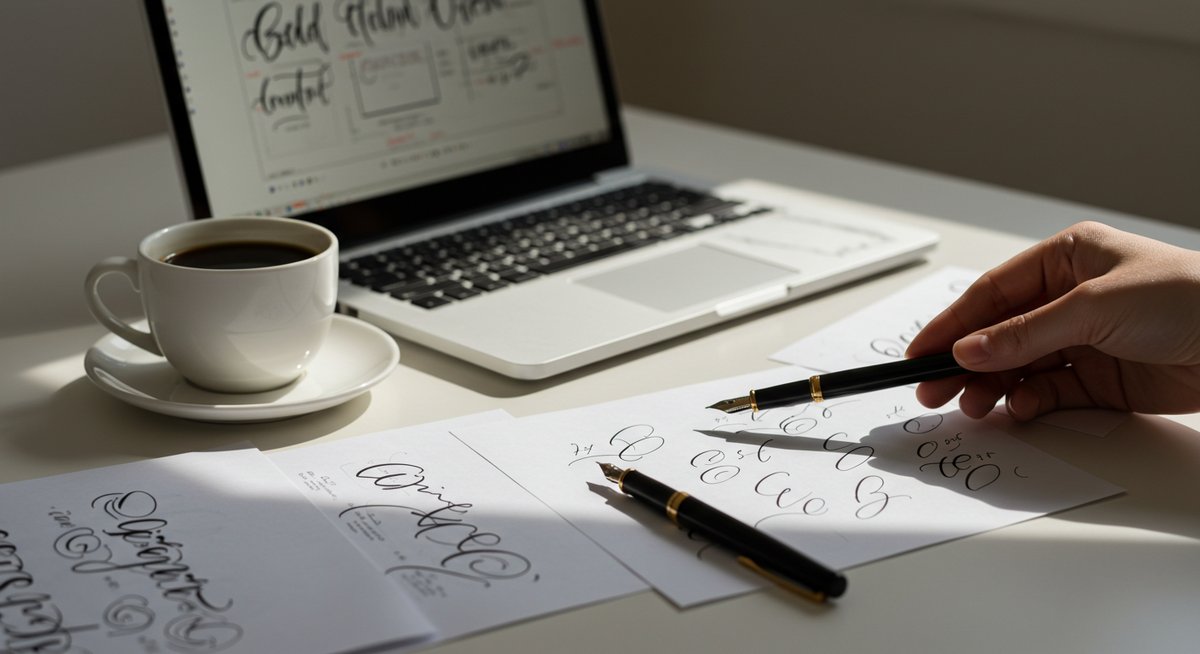
anvaで使える筆記体フォントを選ぶときは「見た目の好み」と「用途」を両方見て決めると失敗が少ないです。この記事では、用途に合わせたおすすめフォントや使い方のポイントをわかりやすく紹介します。どの場面でどんな印象になるかをイメージしながら選べば、デザインの仕上がりがグッとよくなります。
迷わず選べる Canvaで使う筆記体のおすすめ5選
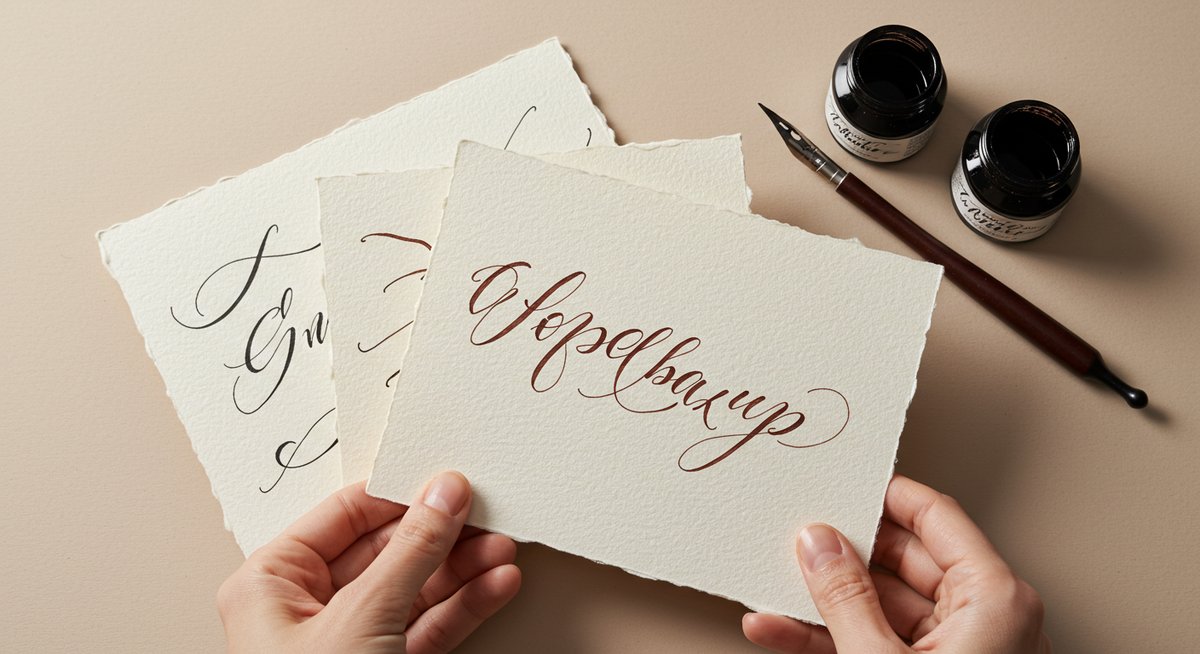
どれを使えば良いか迷ったときに頼れる筆記体を5つピックアップしました。それぞれの特徴と向いている用途を短くまとめています。まずはここから試してみると失敗が少ないですよ。
Allura 無料で上品な定番フォント
Alluraは細めで流れるような線が魅力の筆記体です。角が柔らかく、文字同士のつながりが自然なので、上品で落ち着いた印象を与えたいときに向いています。ロゴや見出し、ウェブサイトのアクセントに使うと、しっかりした高級感を出せます。
読みやすさも比較的よく、小さめのサイズでも崩れにくいのが特徴です。文字間隔を少し詰めるだけで統一感が出るので、見出しやバナーのアクセントにおすすめです。色はダーク系や落ち着いたトーンと相性が良く、シンプルな背景に置くと映えます。
使う場面の例としては、ショップのブランドロゴ、ギフトカード、ブログの見出しなどが挙げられます。フォント自体が主張しすぎないため、他の要素と合わせやすい点も魅力です。
Alex Brush 上品で読みやすい筆記体
Alex Brushは比較的太めの線で、筆致がはっきりしている筆記体です。曲線が滑らかで視認性が高く、装飾的でありながら読みやすさを保ってくれます。そのため、タイトルや重要なフレーズに使うと効果的です。
文字の輪郭がはっきりしているので、背景が多少賑やかでも視認性を確保しやすいです。大きめの見出しや告知バナーに向いており、色を濃くすることでさらに存在感を出せます。行間や文字間を調整すれば、親しみやすい印象からエレガントな印象まで幅広く対応できます。
ブランド名や商品名を目立たせたいとき、又はイベントタイトルなどで使うと、読みやすさとデザイン性の両方を満たせます。
Pacifico カジュアルで親しみやすい筆記体
Pacificoは丸みを帯びた手書き風の筆記体で、明るくフレンドリーな雰囲気を作りやすいフォントです。堅苦しくならないので、カジュアルなショップロゴやSNSの見出しにぴったりです。
太めの線と丸い形状は、小さな画面でも視認性が高く、親しみやすさを強調したいときに便利です。背景に写真を使う場合は、コントラストを強めに取ると読みやすくなります。色使いもポップなトーンに合わせやすく、若い層向けのデザインに向いています。
メニューや商品ラベル、イベント告知など、気軽さや楽しさを伝えたい場面で活躍します。装飾を控えめにしてフォントを主役にする使い方がおすすめです。
Pinyon Script 華やかに飾る見出し向け
Pinyon Scriptは装飾性の高い筆記体で、華やかな印象を与えるのに向いています。しなやかなカーブと装飾的な終端が特徴で、特別な場面や格式感が欲しいデザインにマッチします。
大きめの見出しや招待状のタイトルに使うと、エレガントで印象的な雰囲気を演出できます。繊細なラインが多いので、小さなサイズには向きませんが、大きく表示することで美しさが際立ちます。背景はシンプルにして、フォントのディテールを見せると効果的です。
色はゴールド系やダークカラーと合わせると上品さが増します。結婚式の招待状や高級感を出したい商品パッケージなどに向いています。
Halimum 小さなアクセントに使いやすい筆記体
Halimumは控えめで細やかな筆記体です。大きく主張しすぎないため、ロゴの一部やワンポイントのアクセントに最適です。柔らかく落ち着いた線で、全体のバランスを壊さずに雰囲気を添えてくれます。
小さめの注釈やサブタイトル、名刺の一部などに使いやすく、他のフォントと組み合わせても喧嘩しにくいのが利点です。色は淡めのトーンでも馴染みやすく、ページのアクセントとして自然に溶け込みます。
細めのフォントなので、背景とのコントラストに気をつけると見やすさを保てます。全体のデザインを邪魔せず、ちょっとした個性を出したいときに役立ちます。
用途で選ぶと失敗しない筆記体の選び方
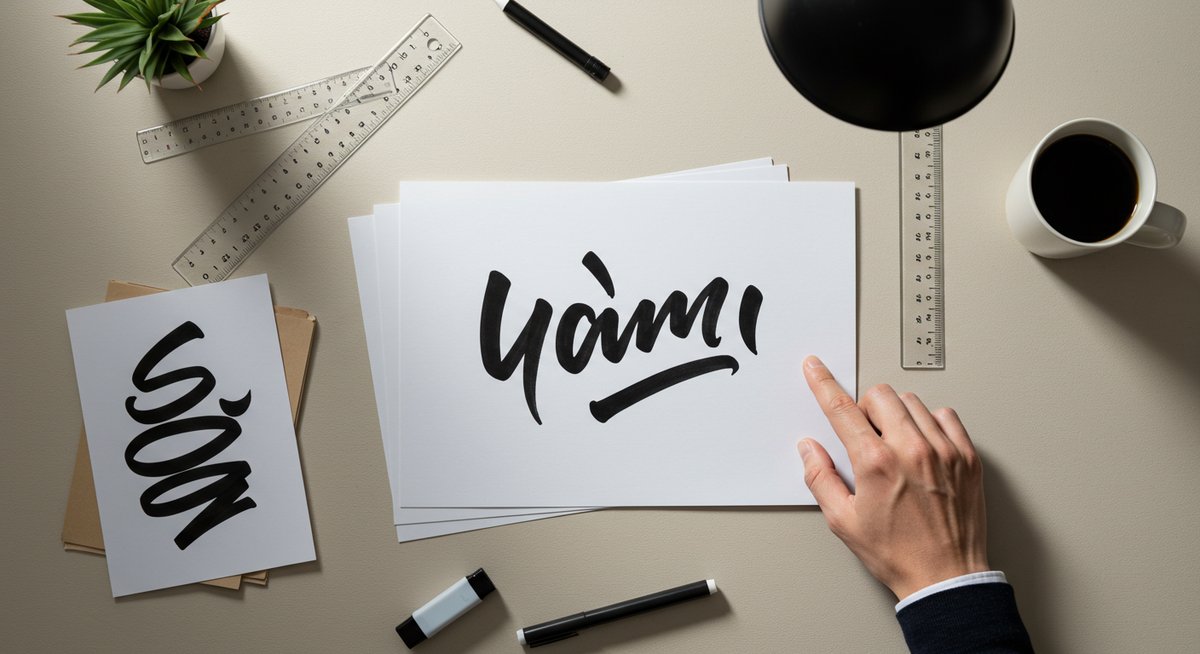
フォント選びは、どこでどんな目的で使うかを考えるのがポイントです。ここでは用途別に押さえておきたいポイントをまとめました。これを基準にすると、使ってから後悔するリスクが減ります。
ロゴやブランドに合う筆記体の条件
ロゴやブランドに使う場合、視認性と一貫性が重要です。まずは遠目でも読める太さや字間を持つフォントを選びましょう。流麗すぎる装飾が多いと、縮小時に判読しづらくなることがあります。
もう一つはブランドの印象に合うかどうかです。高級感を出したければ細く伸びのあるフォント、親しみやすさを出したければ丸みのあるフォントを選ぶと良いです。ロゴは単色での見え方も確認して、背景が変わってもバランスが保てるものを選びましょう。
最後に汎用性です。ロゴは名刺やSNSアイコンなど多くの場面で表示されるため、小さい表示でも読めるかをチェックする習慣をつけると安心です。
見出しやバナーで映える使い方
見出しやバナーではインパクトが大事ですが、目立たせつつ読みやすさをキープすることが大切です。太さやサイズを大きめに設定し、文字間をやや詰めるとまとまりがよくなります。
背景が写真の場合は文字にシャドウやアウトラインを付けて視認性を高めると良いでしょう。色は背景と十分なコントラストを取るのが基本です。複数の要素がある場合は、筆記体を強調し、他のテキストはシンプルなゴシック系にすると見やすくまとまります。
見出しだけでなく、余白も意識するとデザイン全体が整います。余白があると筆記体の美しさが引き立ちます。
本文や説明文に向かない筆記体の見分け方
本文に使う場合は可読性が最重要です。文字の間隔が狭すぎたり、装飾が多すぎるフォントは長文には向きません。小さなサイズで崩れやすいフォントや、似た文字同士(lやI、1など)の判別がつきにくいものは避けましょう。
読みやすさを確認するコツは、実際に複数行打ち込んでスマホ表示でチェックすることです。視認性が落ちるなら見出しだけに使うなど使い分けを考えてください。説明文や長い案内文は、シンプルなフォントを基本にして、筆記体はアクセント程度に留めると読み手に親切です。
SNS投稿で目立たせる色とサイズの決め方
SNSはスクロールが早いので、まず目を引く色とサイズが重要です。背景写真がある場合は明るめの文字色か、文字の周りに薄い影や半透明のブロックを置いて視認性を確保します。文字サイズはモバイルで見たときに読みやすい大きさを基準にしてください。
色はブランドカラーをベースに使うと統一感が出ます。アクセントカラーを1色決め、タイトルに使うと視線を集めやすくなります。複数行になる場合は改行位置を工夫して読みやすくしましょう。
招待状や名刺で映える組み合わせ例
招待状や名刺では上品さと読みやすさのバランスが大切です。筆記体はタイトルや名前に使い、それ以外の住所や連絡先はシンプルなセリフやゴシック系にすると安心です。
カラーはベースに落ち着いたトーンを使い、筆記体はアクセントカラーで強調します。たとえば、ネイビーの背景にクリーム色の筆記体、もしくはホワイト背景にダークグレーの筆記体などが使いやすい組み合わせです。余白を十分に取ると高級感が出ます。
デザインの雰囲気別に似合う筆記体
フォントは雰囲気作りの重要な要素です。ここでは代表的な雰囲気ごとに合う筆記体の特徴をまとめました。目的のイメージに近いものを選ぶとデザインがまとまります。
ナチュラルで優しい雰囲気に合う筆記体
ナチュラルな雰囲気には、丸みがあり線の変化が穏やかな筆記体が合います。筆圧の強弱が控えめで、読みやすさと柔らかさを両立するタイプを選ぶと落ち着いたイメージになります。
色はアースカラーやパステル系が相性良く、背景に植物やテクスチャを使うとさらに馴染みます。装飾を抑えたレイアウトにすると、文字のやさしさが引き立ちます。
用途としては、カフェメニューやナチュラル系ショップの見出し、手作り感のあるパッケージなどに向いています。
エレガントで高級感が出る筆記体
高級感を目指すなら、線の細さと流麗なカーブが特徴のフォントが映えます。文字の終わりに繊細な飾りがあると、さらに格式ある印象になります。
配色はモノトーンや深みのある色をベースに、ゴールドやシルバーのアクセントを加えると豪華さが増します。余白を大きめに取り、文字を単独で見せると洗練された雰囲気になります。
商品ラベルやブランドロゴ、招待状の見出しなどで特に効果的です。
カジュアルで手書き感のある筆記体
カジュアルさを出したいときは、太めでラフな線のフォントがおすすめです。手書きっぽい不揃いさがあると、親しみやすさが出ます。
ポップな色やイラストと合わせるとさらに雰囲気が出ます。背景に写真を使う場合は、文字の輪郭をはっきりさせると読みやすくなります。イベント告知やカジュアルブランドのロゴに向いています。
レトロやヴィンテージに合う筆記体
レトロ感には、装飾がやや多めで古風な端正さが感じられるフォントが合います。太さの変化が明確で、古い看板やラベルを思わせるデザインが雰囲気を出します。
色はセピア系やくすんだ色合いが相性良く、質感のある背景と組み合わせると統一感が出ます。パッケージデザインやカフェのサイン、ヴィンテージ風ポスターに向いています。
モダンでミニマルな空間に合わせる筆記体
ミニマルな雰囲気には、線が細くシンプルな筆記体を選ぶと洗練された印象になります。装飾が少ないことで余白との調和が取りやすく、すっきりとした見た目になります。
配色はモノトーンやグレートーンでまとめ、筆記体は控えめなアクセントにするとモダンさが際立ちます。シンプルなショップロゴやウェブの見出しに向いています。
Canvaで筆記体をより魅力的に見せる操作
フォント自体の選び方に加えて、Canva上での操作も重要です。ここでは押さえておきたい基本操作や設定を紹介します。少しの工夫で見栄えが大きく変わります。
フォントサイズと行間で読みやすさを作る
フォントサイズは表示媒体に合わせて決めましょう。スマホ表示が多いなら少し大きめに設定すると読みやすくなります。見出しは強調するために十分なサイズを取り、本文とのバランスを見てください。
行間は筆記体だと詰まりやすいので、やや広めにすると読みやすくなります。特に縦に長い文や複数行に渡るときは、行間を調整して文字同士の干渉を避けると見やすさが向上します。
文字色と背景のコントラストの作り方
文字の色と背景のコントラストは読みやすさの要です。背景が明るいなら文字は濃い色、背景が暗いなら明るい色を選びましょう。写真背景なら半透明のボックスや薄い影を入れて文字を際立たせると効果的です。
色選びではブランドカラーを基準にしつつ、視認性が高い組み合わせを優先してください。配色が決まらないときは、モノトーンで試してからアクセントカラーを足すと安全です。
複数フォントを組み合わせる基本ルール
複数フォントを使う場合は、最大でも2〜3種類に抑えるのが安全です。筆記体はアクセント役にして、本文は読みやすいサンセリフやセリフ体にすると全体がまとまります。
コントラストを出すために、筆記体は太さやサイズで目立たせ、他のフォントはシンプルにするのが基本です。見出しと本文で役割分担を明確にすると読み手に優しい構成になります。
筆記体フォントでデザインを簡単に格上げ
筆記体は少しの工夫でデザインに個性や温かみを加えられます。まずは用途に合わせてフォントを選び、Canva上でサイズや色、余白を調整してみてください。慣れてくると、ちょっとしたアクセントで全体の印象が大きく変わることが実感できるはずです。